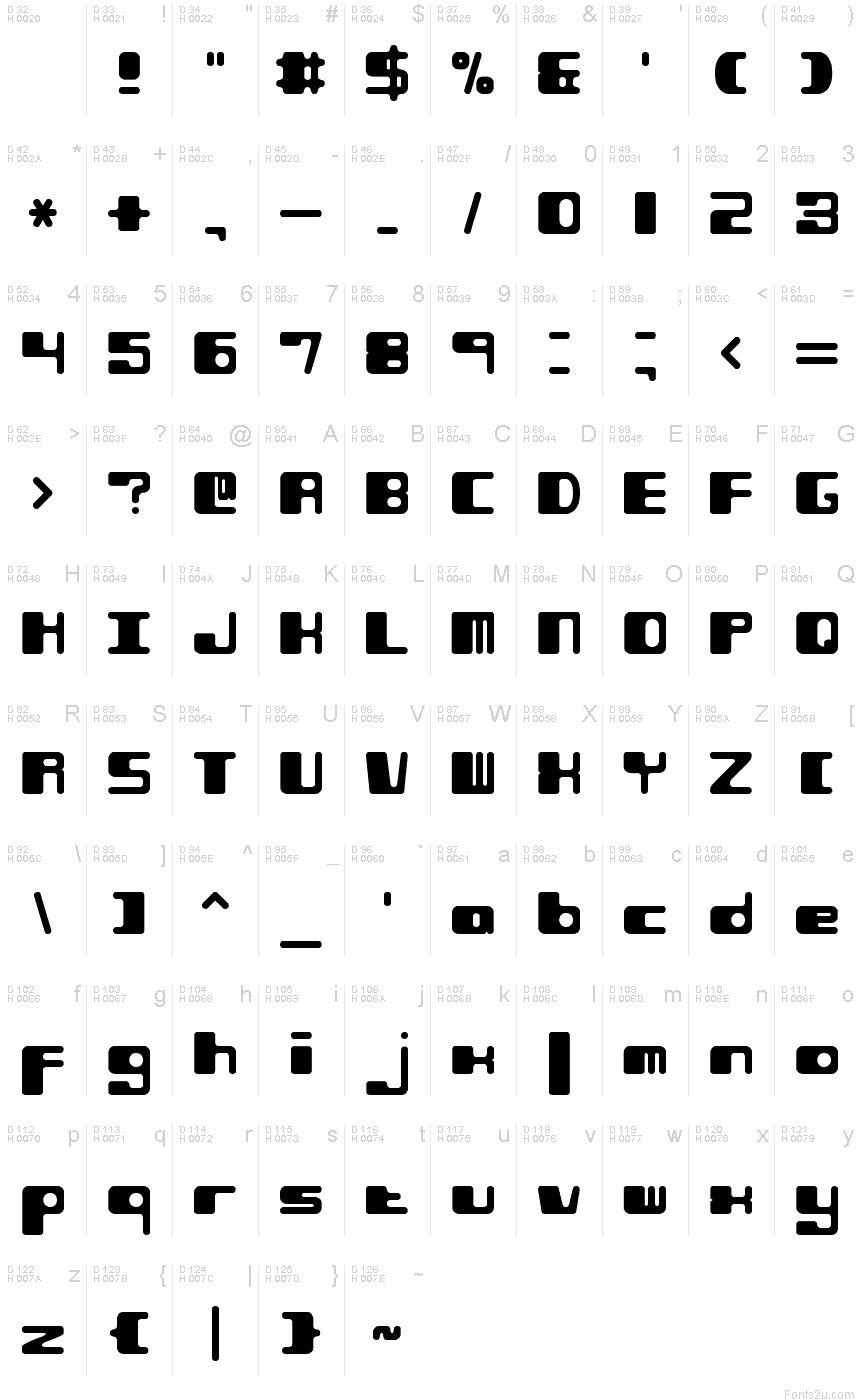
Phorfeit di ÆNIGMA Fonts è un font display techno arrotondato, caratterizzato da un aspetto compatto e scolpito. Le lettere appaiono pesanti ed essenziali, con angoli morbidi, curve squadrate e tagli profondi che conferiscono al font un'estetica da segnaletica retro-futurista, ben lontana dalla solita geometria moderna.
È perfetto per poster, titoli di videogiochi, copertine di dischi, branding di app e loghi brevi in cui bastano pochi caratteri a definire l'atmosfera. Essendo un font gratuito, è ideale anche per copertine, titoli e intestazioni d'impatto, grazie alle sue forme smussate e alle aperture nette che rendono anche le parole più brevi esteticamente studiate e leggermente sintetiche.